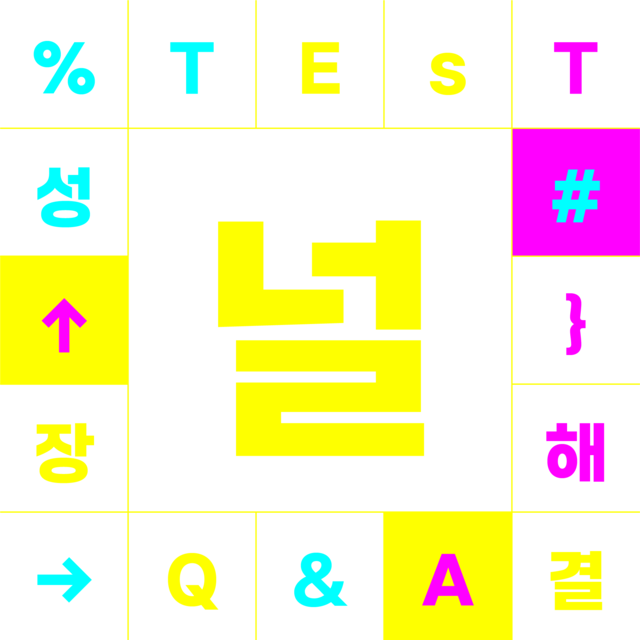
위의 이미지에서 보듯이 엘리스 DX널리체는 직선과 곡선이 어우러진 조화로운 대칭형 디자인으로 제작한 서체로 꽉 찬 네모꼴 형태에 한글과 영문이 안정적으로 배치된다는 특징이 있다. 특히 ㅅ, ㅈ, ㅊ 등이 완만한 곡률로 디자인하면서 자소 하단에 각도를 준 즉, 자소가 받침이 아니라 윗부분에 나올 때 하단 끝부분만 상향하는 형태로 강한 고딕 서체한 부드러운 느낌을 추가하고 있다.
해당 엘리스 DX널리체는 디지털 플랫폼에 최적화한 폰트로 획이 늘어나면 글자 폭 역시 달라지는 가변 폭 모둘을 적용하고 있다. 글꼴 크기에 따라 Light, Medium, Bold 3종의 글꼴로 제공하는 엘리스 DX널리체는 한글 12,3450자에 추가로 430자를 더했으며, 라틴문자 95자와 특수문자 985자로 구성되어 있다.
해당 엘리스 DX널리체는 디지털 플랫폼에 최적화하여 웹, 공간 등 어디에나 어울리는 가독성과 가시성을 모두 고려한 타이틀용 서체로, 고정된 폭이 아니라 자유롭게 폭을 조절할 수 있는 가변 폭 모듈을 적용하고 있다. 이러한 엘리스 DX널리체는 폰트 굵기에 따라 구분한 3가지 글꼴로 제공하는데 주로 윈도우용으로 알려진 ttf 포맷과 맥용으로 알려진 otf 포맷을 제공하고 있다. 즉, 해당 엘리스 DX널리체 다운로드 버튼을 누르면 폰트 라이선스를 비롯하여 ttf 포맷과 otf 포맷을 다운로드할 수 있는 세부 다운로드 항목을 제공한다.